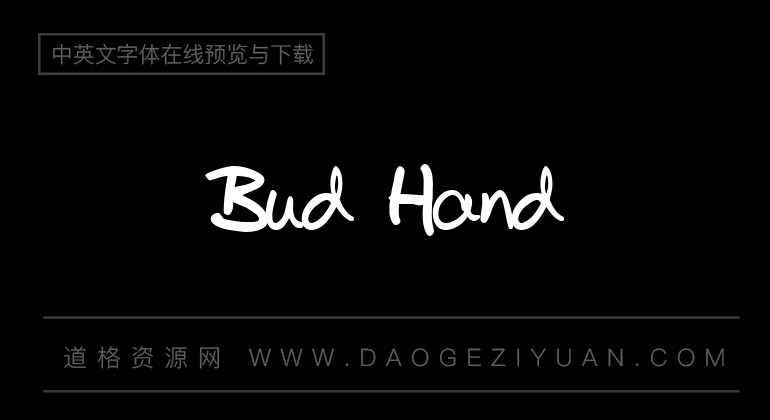
Bud Hand 是一款美式手写体字体,由 Bud Renshaw 设计,于1993年发布。它的特点是每个字母都有一种温暖的、自然的感觉,可以用于简短的标题、标签、卡片或其他文字设计,以及社交媒体或网页设计。它的字重和字形让它很容易识别,而且它的设计也很容易阅读,是一款非常适合用于各种文字设计的字体。内容介绍
Bud Hand是一款非常不错的手写艺术字体,具有很好的视觉感,适合于文化类的宣传设计、商业类品牌的广告和产品包装设计以及个性化文字排版等较多场景。